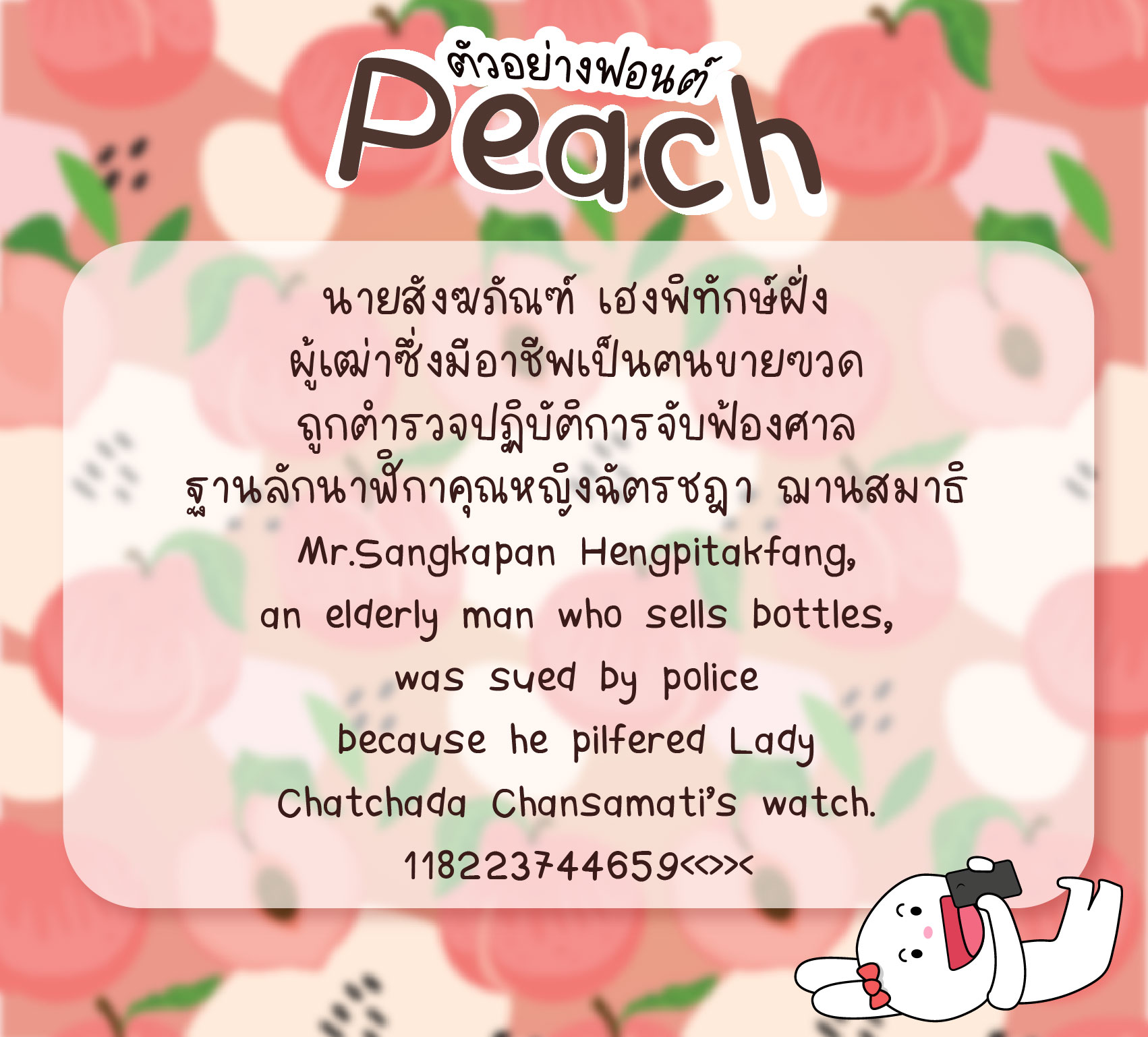
ลูกพีช (lookpeach)
ชื่อฟอนต์ : ลูกพีช
ฟอนต์ลูกพีช สุดคิ้วววทึ มีด้วยกัน 4 น้ำหนัก (ตัวปกติ ตัวหนา ตัวเอียง และตัวหนาเอียง)
สามารถใช้ได้ทั้งภาษาไทย และภาษาอังกฤษ มีเลขอาราบิก เลขไทย  และสัญลักษณ์ทางคณิตศาสตร์ อื้อหือ! สุดปัง!